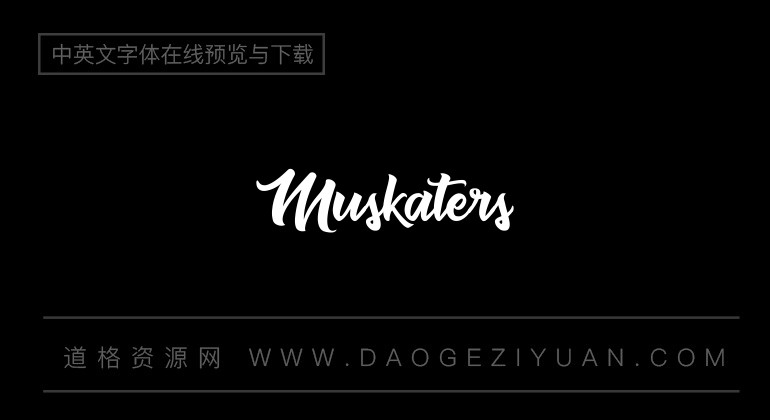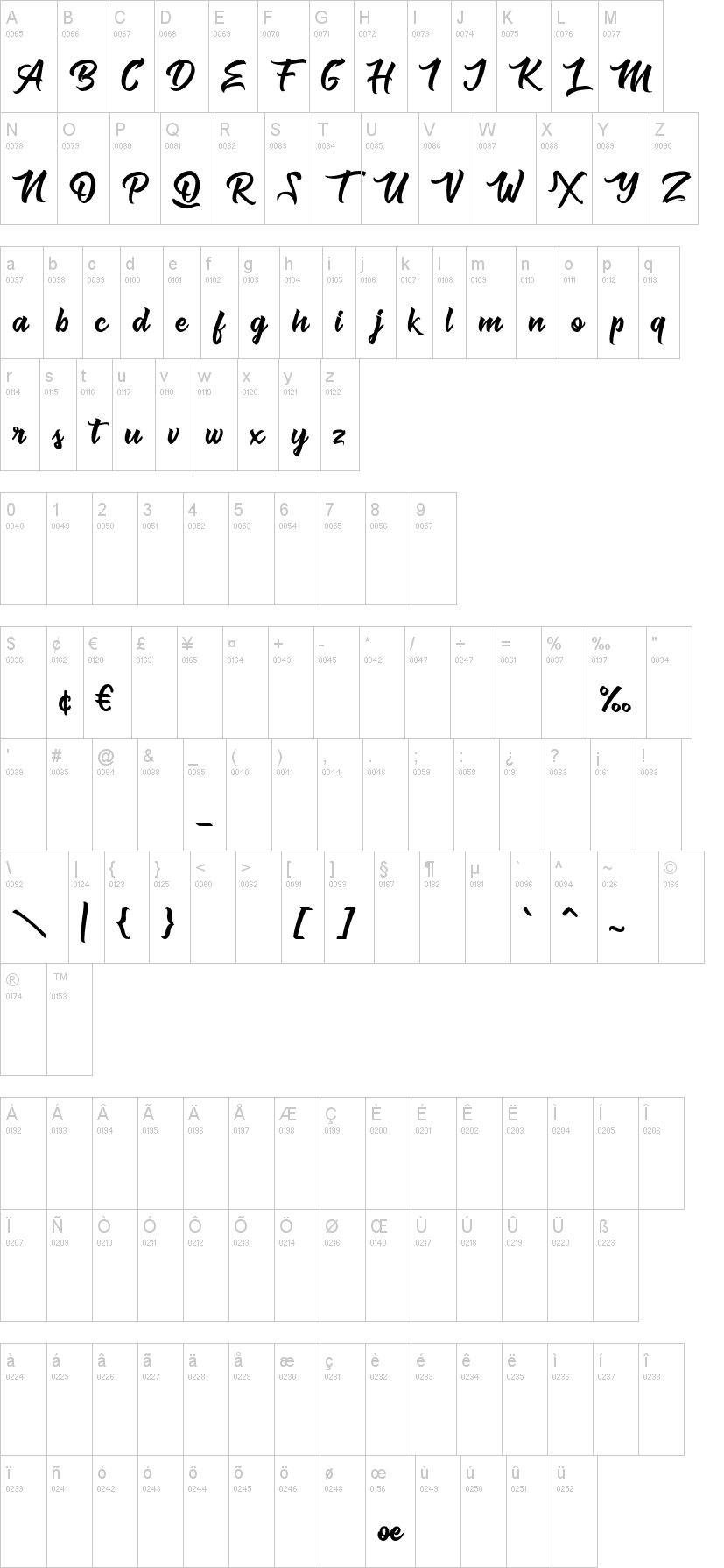
Muskaters
Muskaters 是一款极具特色的英文字体,它具有粗犷、灵动和复古的风格,同时又不失精致,可以用于各种设计项目,如标志、海报、印刷和网页设计等。它的特点是具有较高的可读性和视觉冲击力,可以让你的设计更加醒目,吸引更多的眼球。
Muskaters是一款非常不错的手写艺术字体,具有很好的视觉感,适合于文化类的宣传设计、商业类品牌的广告和产品包装设计以及个性化文字排版等较多场景。
Muskaters字符映射图